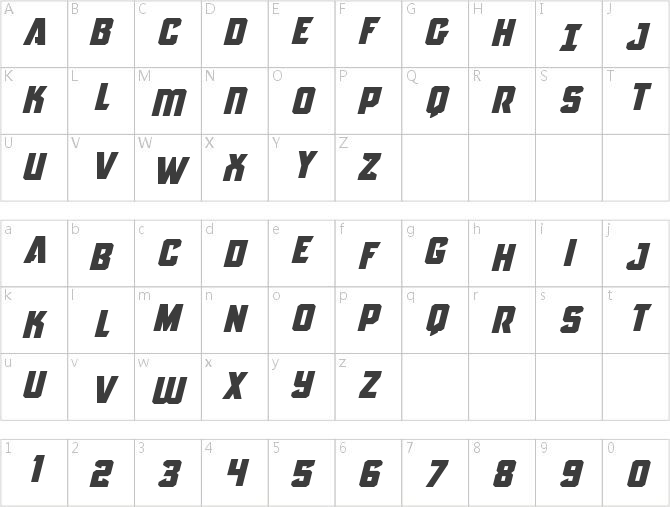
字體名稱: antille
antillesexpandital
antillesexpandital介紹
antillesexpandital字體字庫是一款讓人賞心悅目、百看不厭的英文字體,適合各類廣告和產品包裝設計應用,字體大小0.02MB,格式為ttf字體,上傳用戶是速拓科技,作者/版權方為未知